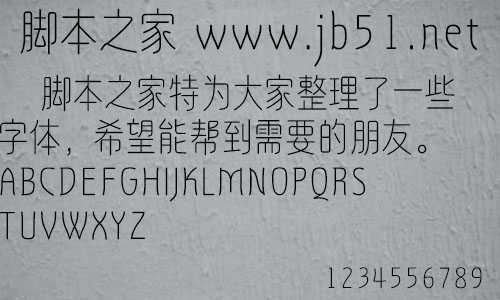
漢儀天諾麗線簡/繁一款不錯(cuò)的藝術(shù)字體,由漢儀字庫出品,字體筆觸纖細(xì),字形端正,具有很好的視覺感,適合應(yīng)用于藝術(shù)設(shè)計(jì)、平面宣傳設(shè)計(jì)、網(wǎng)頁設(shè)計(jì),書法字帖等領(lǐng)域,需要的朋友可以前來本站下載。